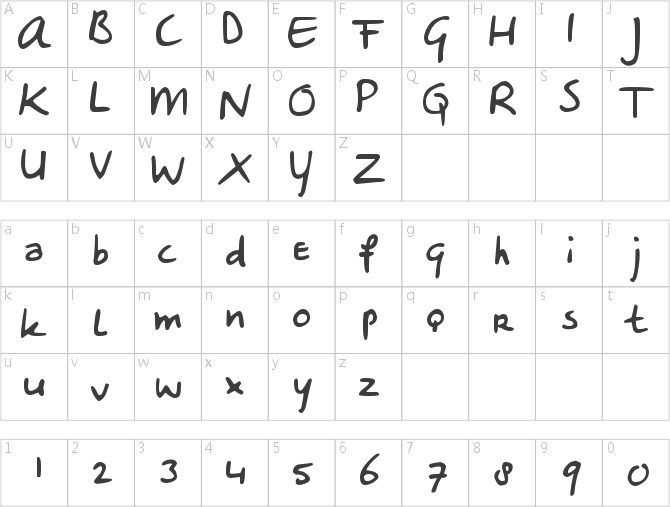
DJB Sheldon's Girlfriend
DJB Sheldon's Girlfriend介紹
DJB Sheldon's Girlfriend字體字庫是一款讓人賞心悅目、百看不厭的英文字體,適合各類廣告和產品包裝設計應用,字體大小0.03MB,格式為ttf字體,上傳用戶是高塔。,作者/版權方為未知